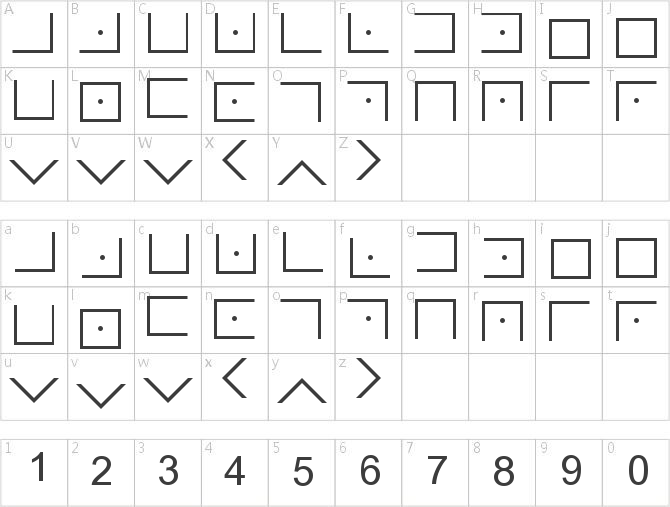
Illuminati Masonic Cipher
Illuminati Masonic Cipher介绍
Illuminati Masonic Cipher字体字库是一款让人赏心悦目、百看不厌的英文字体,适合各类广告和产品包装设计应用,字体大小0.02MB,格式为ttf字体,上传用户是wo~,作者/版权方为未知